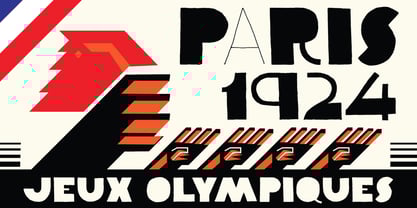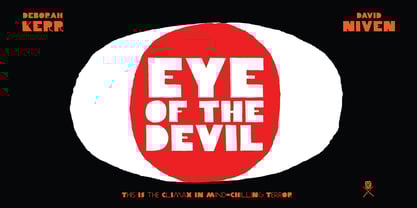
YWFT Clairemy
von YouWorkForThem
YWFT Clairemy Font Familie war entworfen von veröffentlicht von YouWorkForThem. YWFT Clairemy enthält 1 Stile.
Über YWFT Clairemy Font Familie
Der Geruch von Tinte liegt in der Luft, während die Widerstandsdrucker tief in einem Keller im französischen Viertel Propaganda betreiben. Der Absinth fließt in Strömen, und das Radio rauscht, während die YWFT Clairemy ihre stolze und lebendige Präsenz kundtut. Handgezeichnet in der Nachtluft mit einem DC-3-Propellerblatt, ist YWFT Clairemy 327 Glyphen reiner, bistromatischer Ruhm und enthält OpenType-Alternativen, die DeGaulle dazu bringen würden, seinen Schnurrbart zu stutzen. Die Trompeten erklingen. Entworfen von Blake E. Marquis & YouWorkForThem.